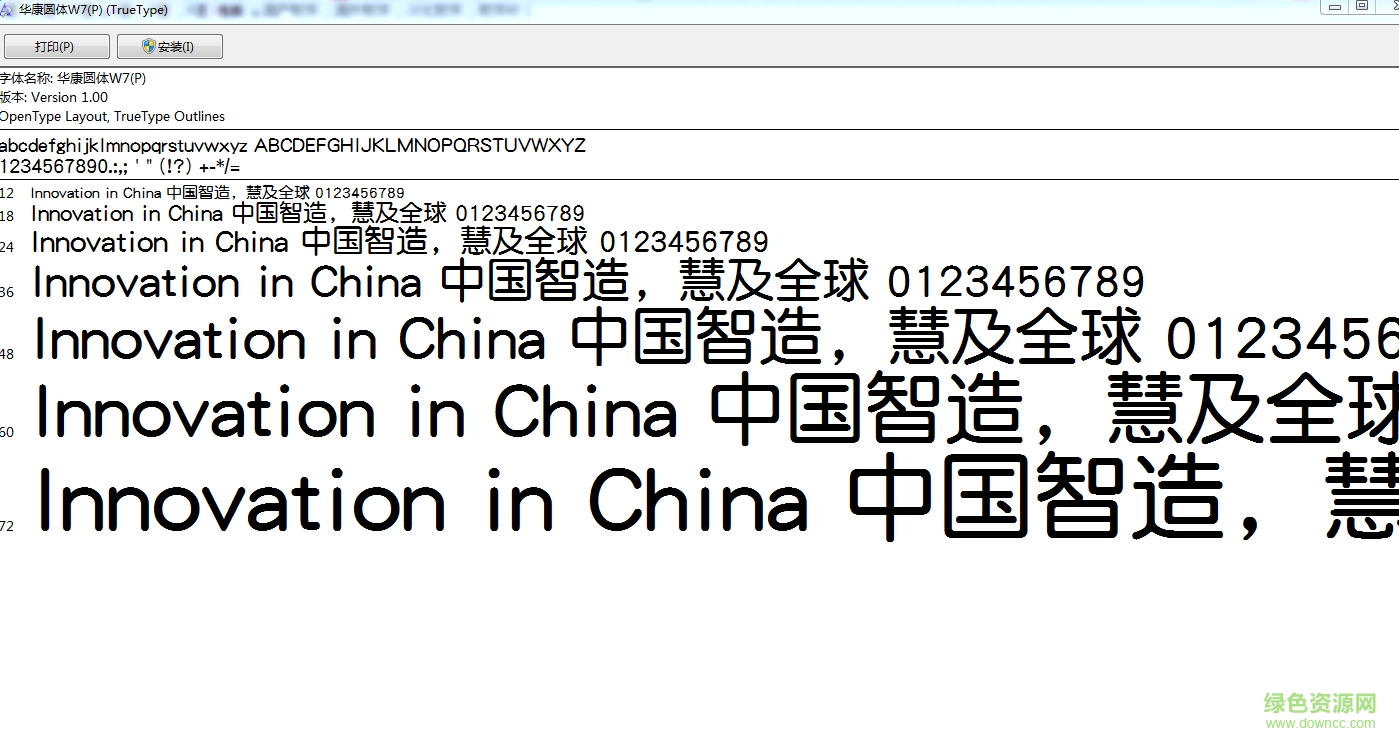
dfpyuanw7是什么字體?dfpyuanw7字體其實就是華康圓體w7,該字體邊角圓潤,線條柔和,結(jié)構(gòu)勻稱,很多領域都可以用得到這款字體,喜歡的朋友快來綠色資源網(wǎng)下載吧!
dfpyuanw7字體是一款藝術設計方面的中文簡體漢字,柔合了黑體的簡潔加添了圓混柔和之感觀,字型筆劃簡單,圓頭圓尾,骨格外張內(nèi)弛,反明黑內(nèi)文字之嚴肅氣氛。細圓于排內(nèi)文時感覺特別均衡,字行感額外明顯。效果非常美觀,且結(jié)構(gòu)統(tǒng)一,可應用于繪畫設計、藝術創(chuàng)作、平面廣告、印刷包裝等方面。